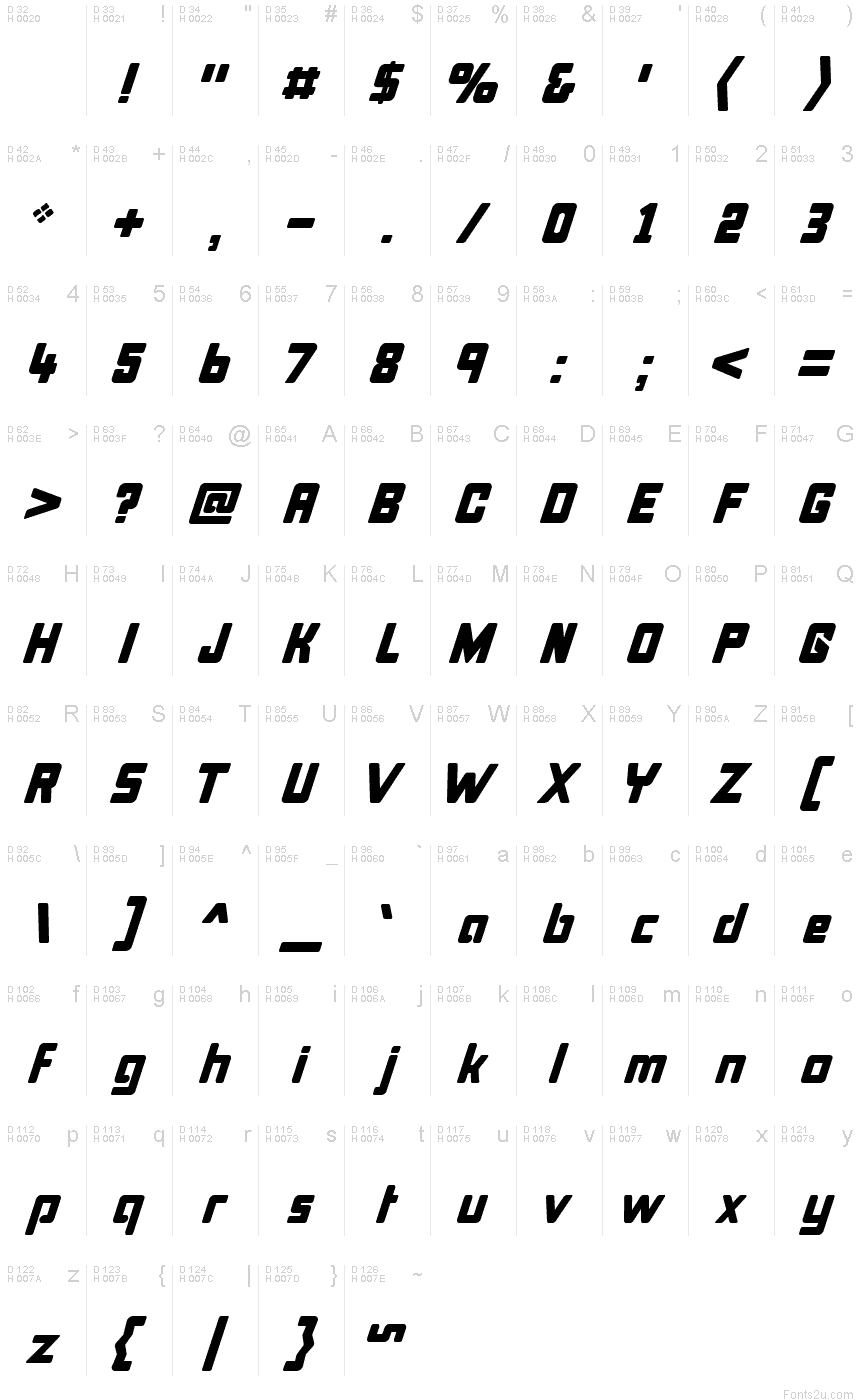
Bonk Italic od Rolfa Schoebera to darmowy, pochylony krój typu techno z grubymi, ukośnymi literami, które wyglądają, jakby zostały figlarnie przesunięte wzdłuż linii bazowej. Odważne, blokowe kształty i wąskie światła wewnętrzne nadają całości energetyczny, wyrazisty charakter – czytelny nawet w małych rozmiarach, a przy tym głośny i zabawny w dużej skali.
Używając Bonk Italic, nadasz żywy i nieszablonowy ton brandingowi dla dzieci, tytułom komiksów, interfejsom gier, miniaturom na YouTube, naklejkom czy plakatom. Gładkie, ciężkie formy sprawiają, że ten darmowy font świetnie sprawdza się w przyciągających wzrok nagłówkach i krótkich hasłach, zwłaszcza gdy zestawisz go z prostym, neutralnym bezszeryfowym krojem w tekście głównym, pozwalając mu wybrzmieć w większych rozmiarach.